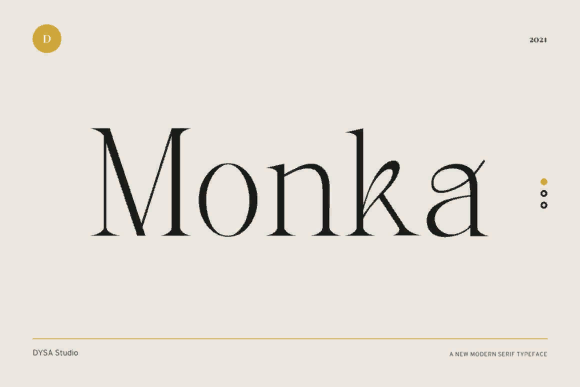
Название: Monka Font (2021)
Monka - это современный и чрезвычайно уникальный шрифт с засечками, отлично подходящий для бизнеса или брендинга.
Он идеально подходит для всех, кому нужен чистый, современный, минималистичный, элегантный и красивый шрифт!
Название: Monka Font (2021)
Monka - это современный и чрезвычайно уникальный шрифт с засечками, отлично подходящий для бизнеса или брендинга.
Он идеально подходит для всех, кому нужен чистый, современный, минималистичный, элегантный и красивый шрифт!